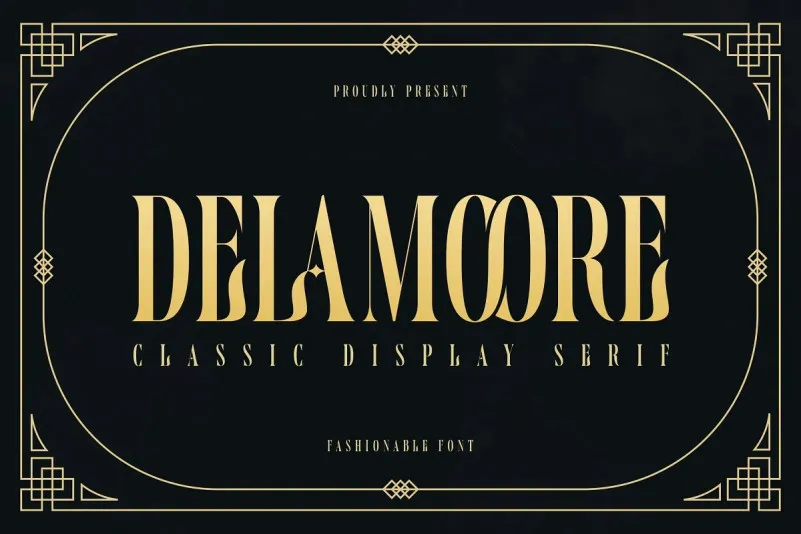
A fonte Delamoore é uma elegante tipografia serif que se destaca pelo uso de ligaturas para ligar com suavidade letras uns aos outros. Suas origens vintage conferem um toque interessante a logotipos, tornando-os mais criativos e únicos. Com suporte multilíngue e suas singularidades gráficas inspiradas na arte decorativa do movimento arquitetônico, Delamoore é uma escolha ideal para qualquer designer buscando dar um toque vintage e moderno a seus projetos. Esta fonte traz ao seu projeto um charme sofisticado que certamente impressionará os usuários finais. Seja para criar rótulos de embalagem, identidade corporativa ou apenas decorar o texto de sua página web com um estilo inovador, Delamoore é a escolha perfeita para qualquer design.